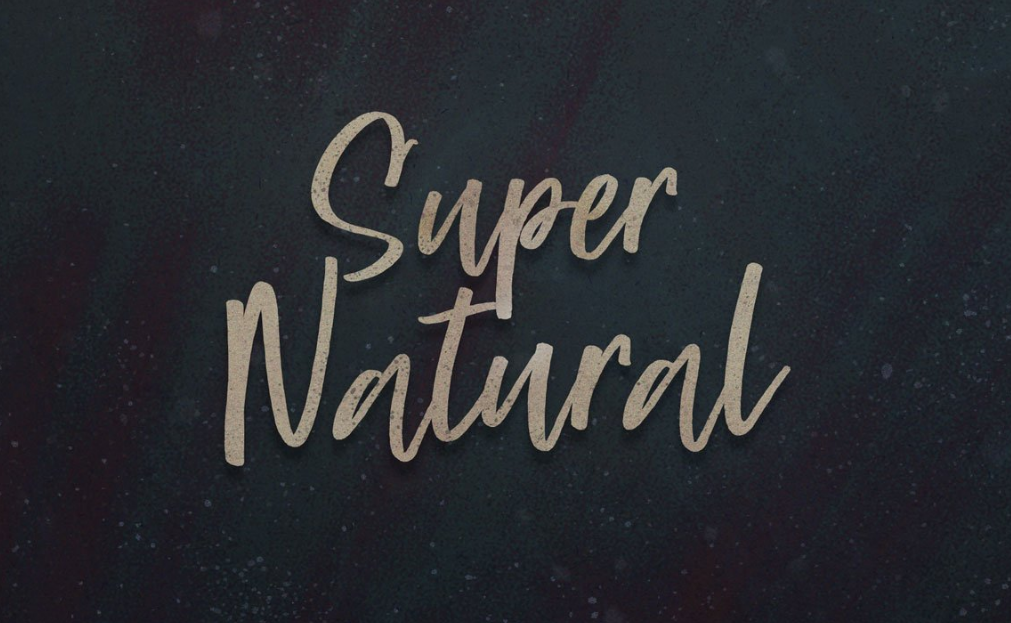
Super Natural Script Font – Download Grátis
A Super Natural Script Font é uma criação cuidadosamente concebida pela proeminente designer BLKBK. Esta fonte script apresenta cada letra com tanto detalhe e atenção aos mínimos pormenores, garantindo que qualquer texto seja apresentado de forma encantadora. Com seu estilo de escrita, esta fonte se destaca para uma variedade de projetos variados como citações, cabeçalhos de blog, cartazes, casamentos, marca, logotipos, moda e roupas, selos, convites e material de correspondência. Estamos certos de que a Super Natural Script Font é um ativo valioso para qualquer designer gráfico em busca de uma fonte perfeita para seu próximo projeto.